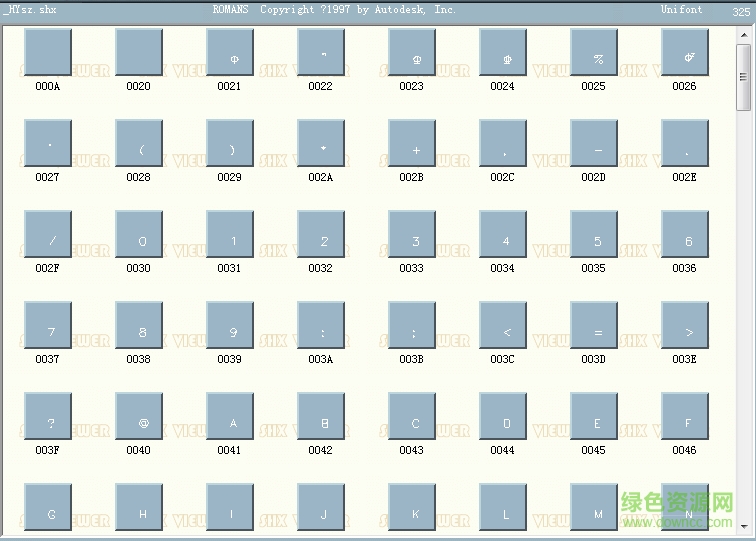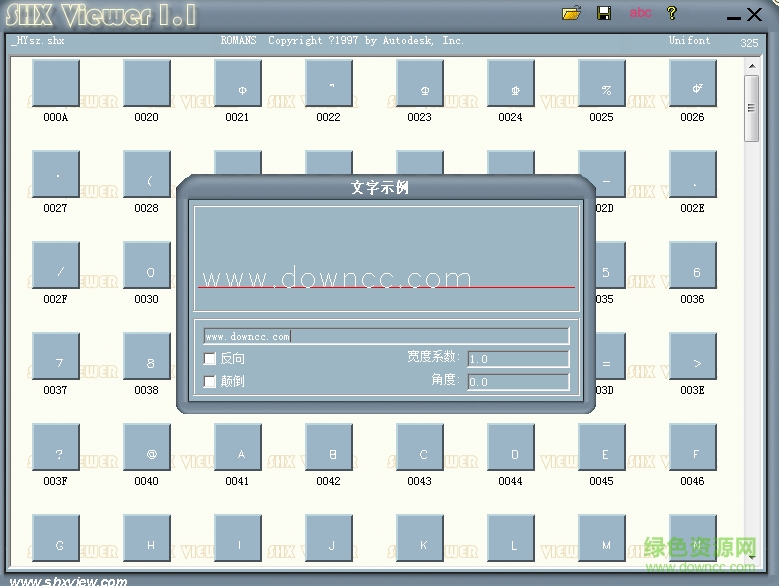
_hysz.shx字體
_hysz.shx 怎么安裝?_hysz.shx用什么替代?hysz.shx字體是autocad建筑結(jié)構(gòu)中的一款稀缺字體,綠色資源網(wǎng)為大家免費(fèi)提供該字體并附帶詳細(xì)的安裝方法,另外hysz.shx字體還可以用gbcbig字體來(lái)替換使用,有需要者快來(lái)下載吧!